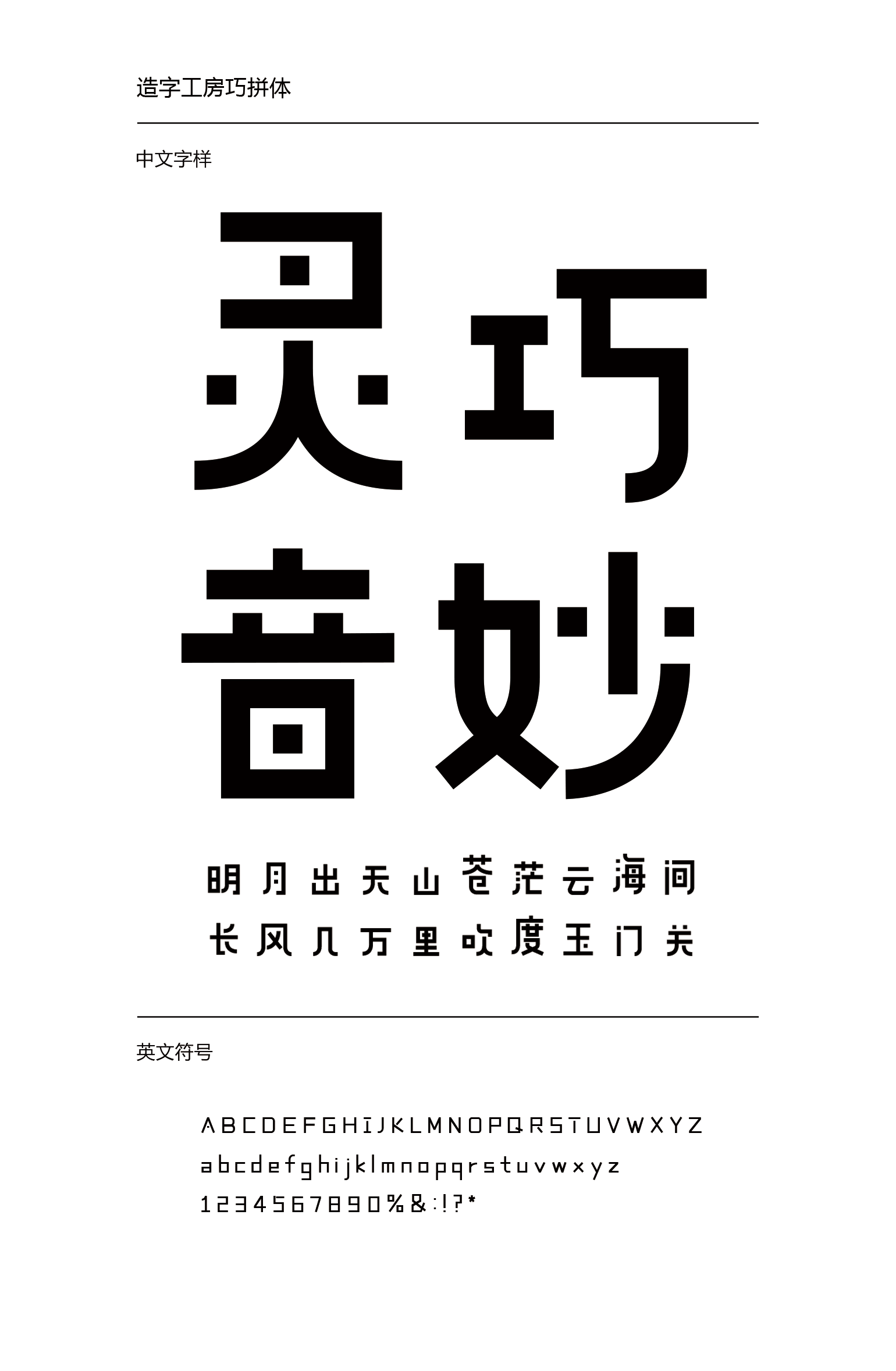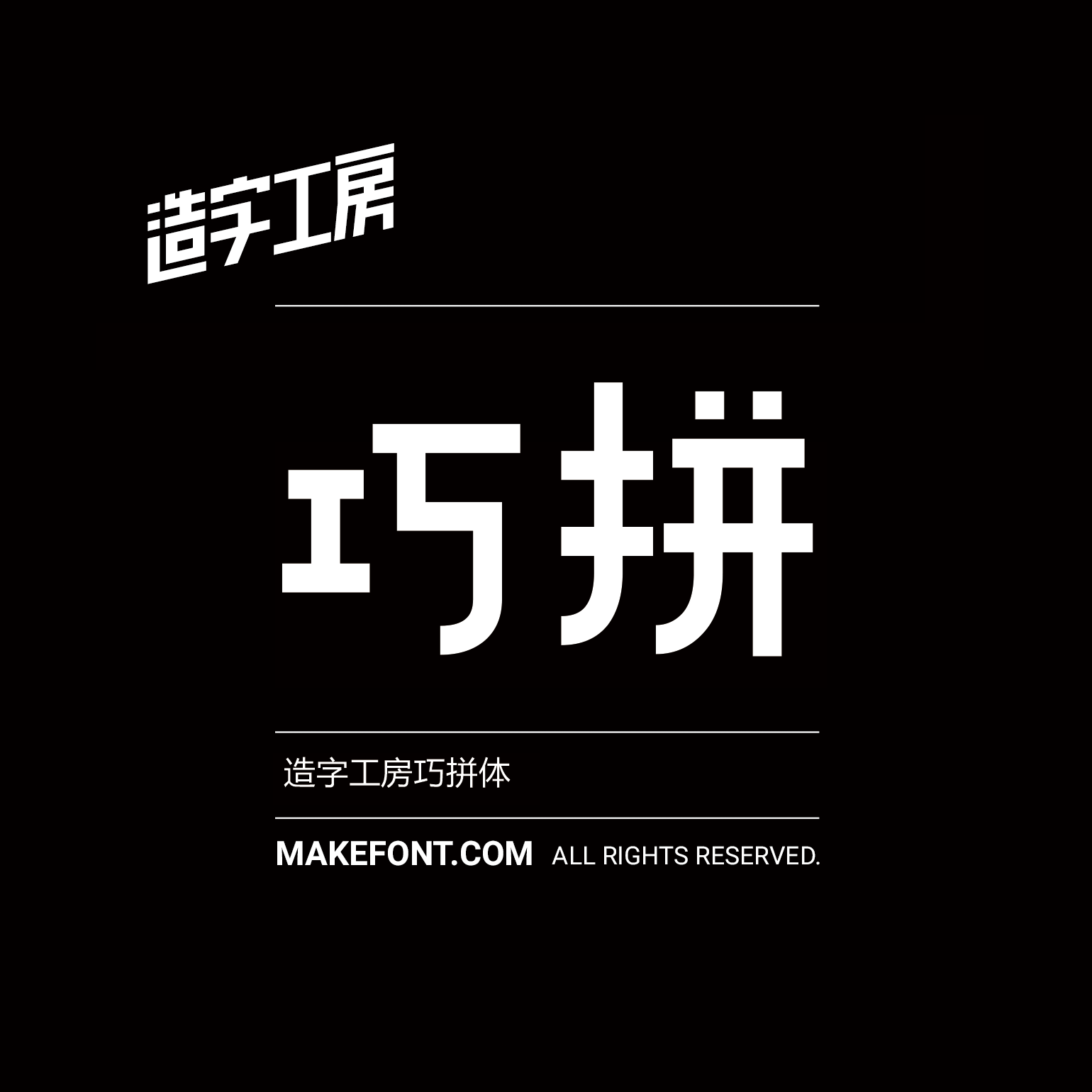
造字工房巧拼体
造字工房巧拼体设计说明
造字工房巧拼体,字形大小错落、疏密得当,简洁方整却又毫无刻板拘泥之感,极富变化的同时却无娇柔造作之姿,笔画粗细均匀,点处理为方点,天真有趣、憨态十足。此款字体适用于儿童读物、报刊杂志标题、广告设计等视觉环境,有着极强的应用空间。本字体为简体字库,采用OpenType/CID格式,Adobe-GB1-5编码。基于中华人民共和国GB2312-80字符集标准,另按需添加101个汉字。共收容字数6864CJK汉字,ASCII常用字符100个。